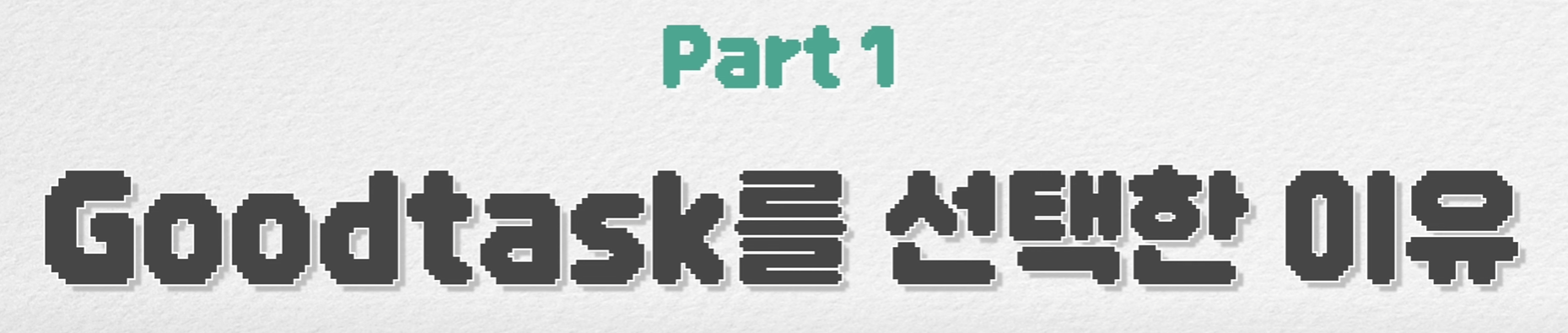
이 폰트 이름 뭘까요?? how*** 2023.07.30 깔끔하게 도트 들어가고 예뻐보여서 알고싶습니다ㅜㅜ 댓글 0 등록 kil*** 던파 비트비트체요! 2023-07-31 답글 달기 how*** 헐 감사합니다!! 2023-07-31 답글 달기 댓글 더보기 쉽고 빠르게 가장 비슷한 폰트를 알고 싶다면? 이미지로 검색하기
던파 비트비트체요!